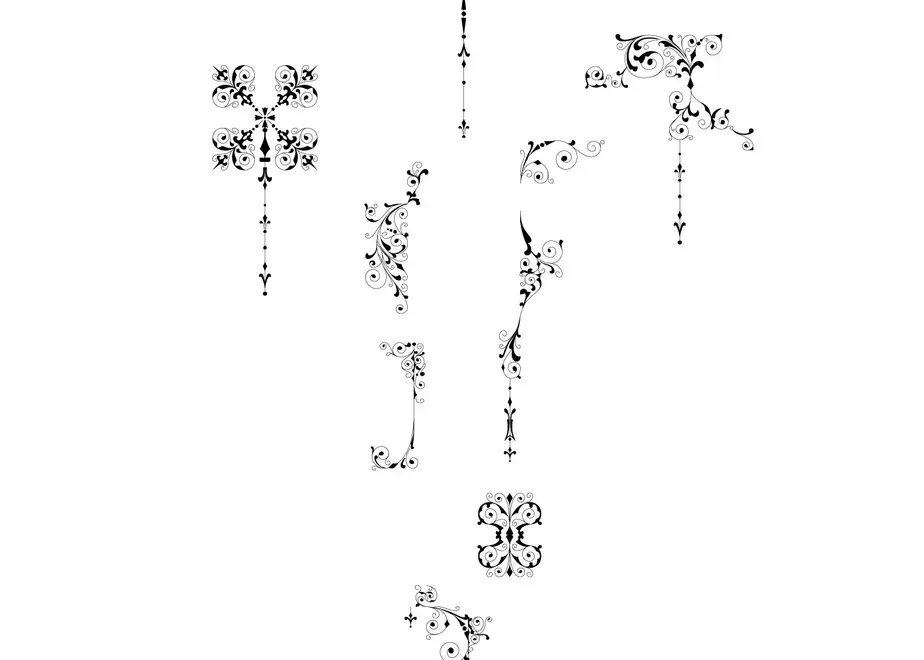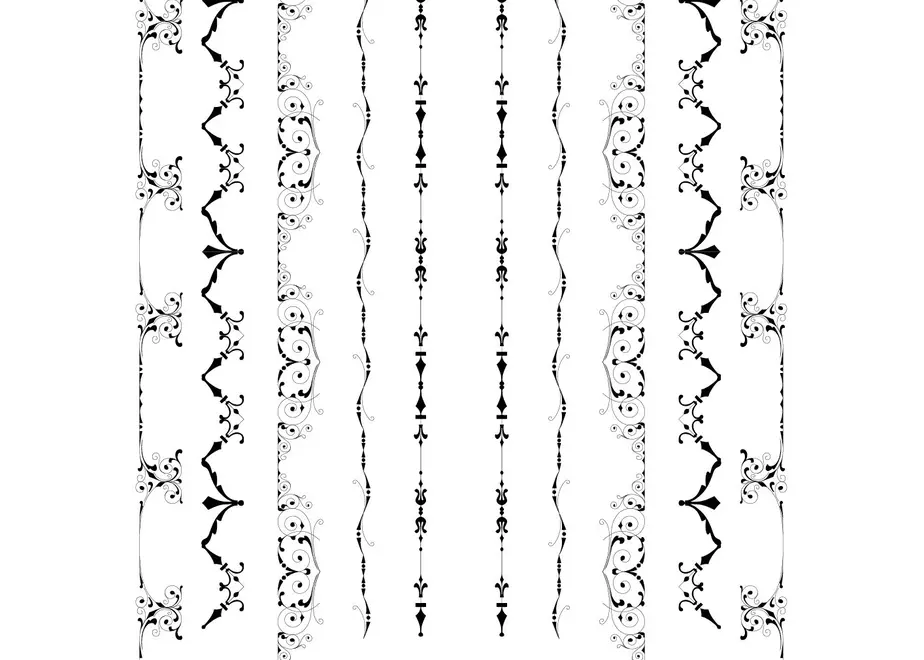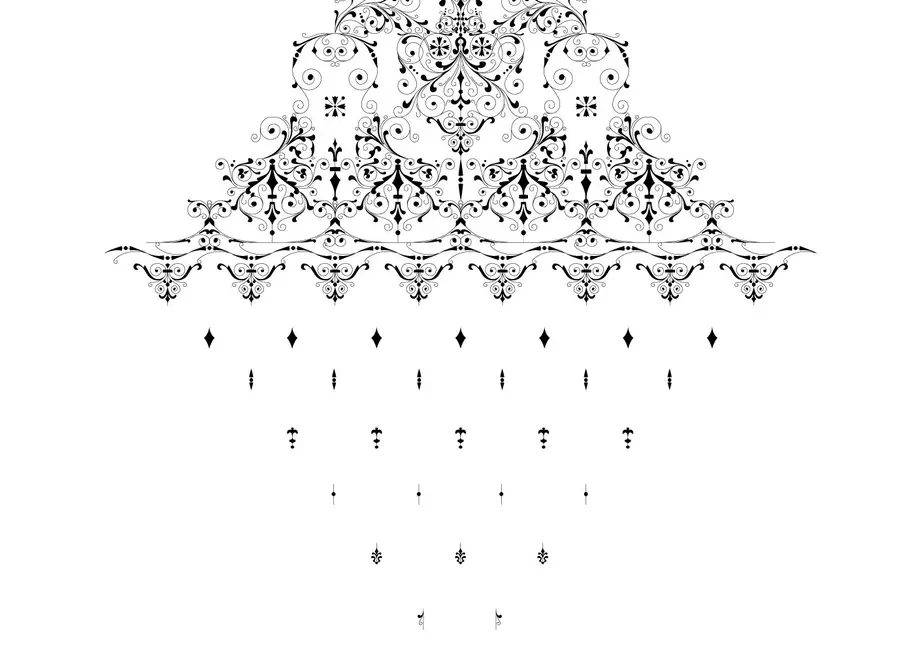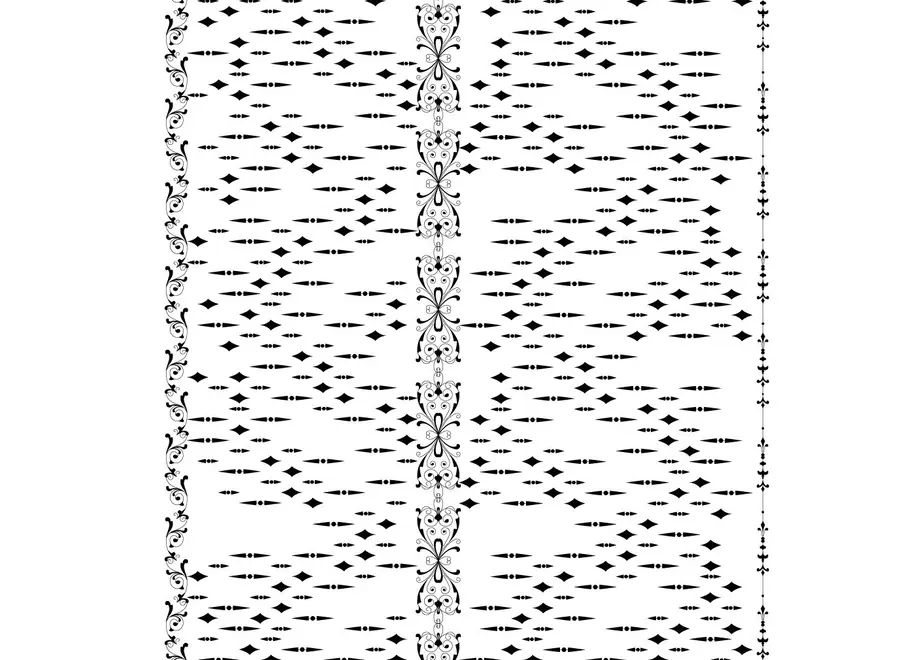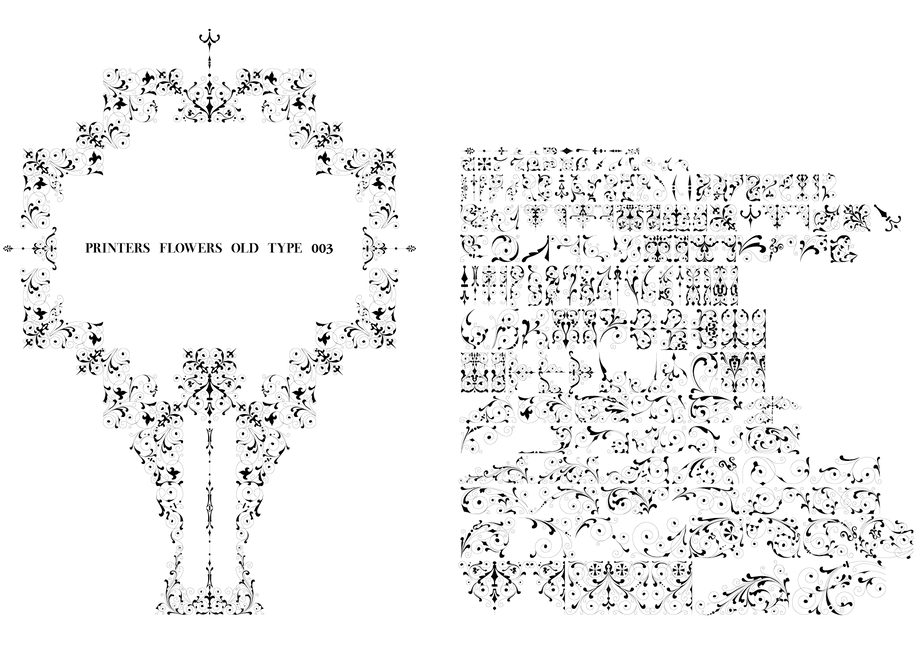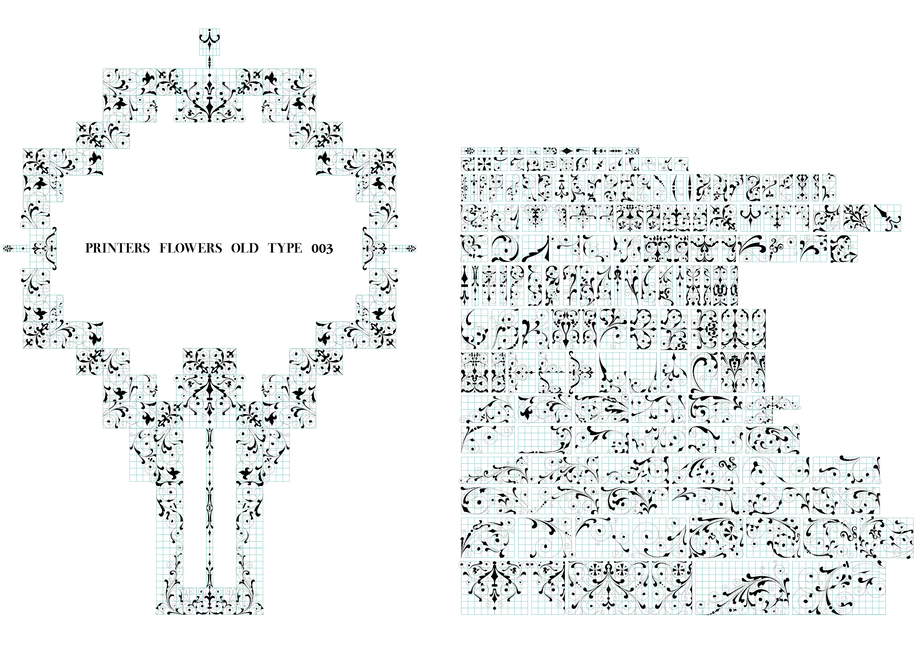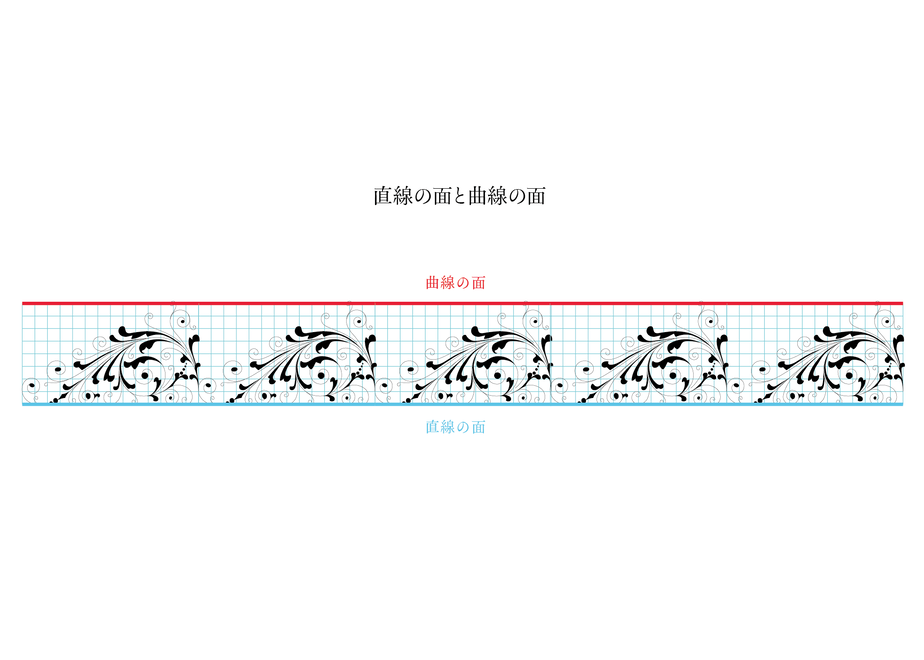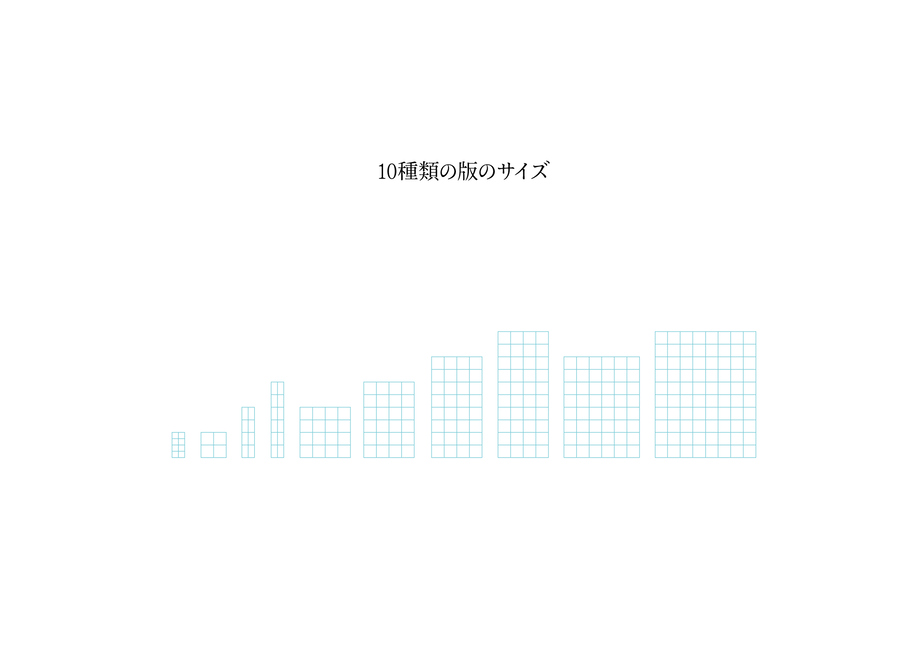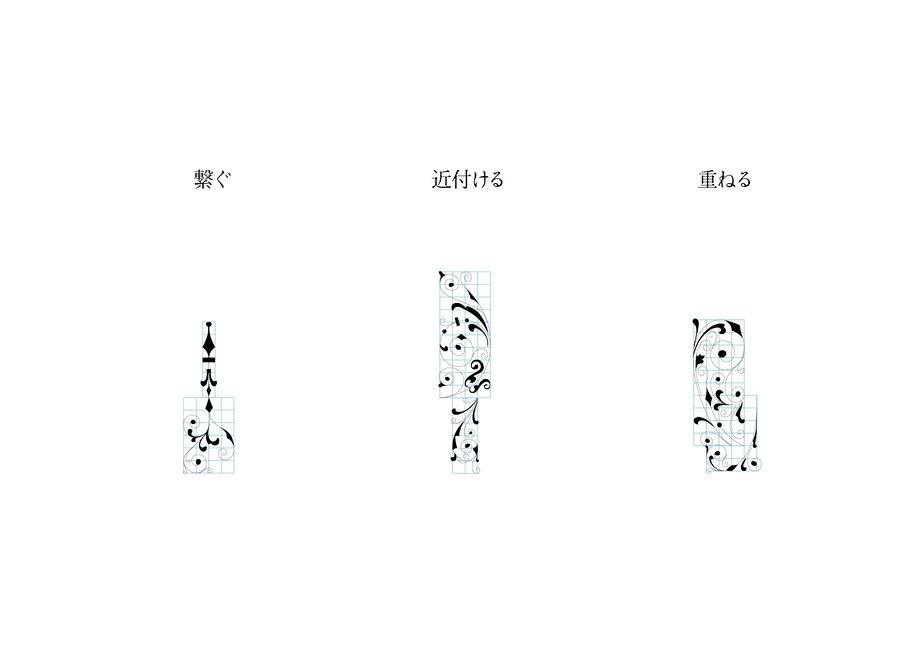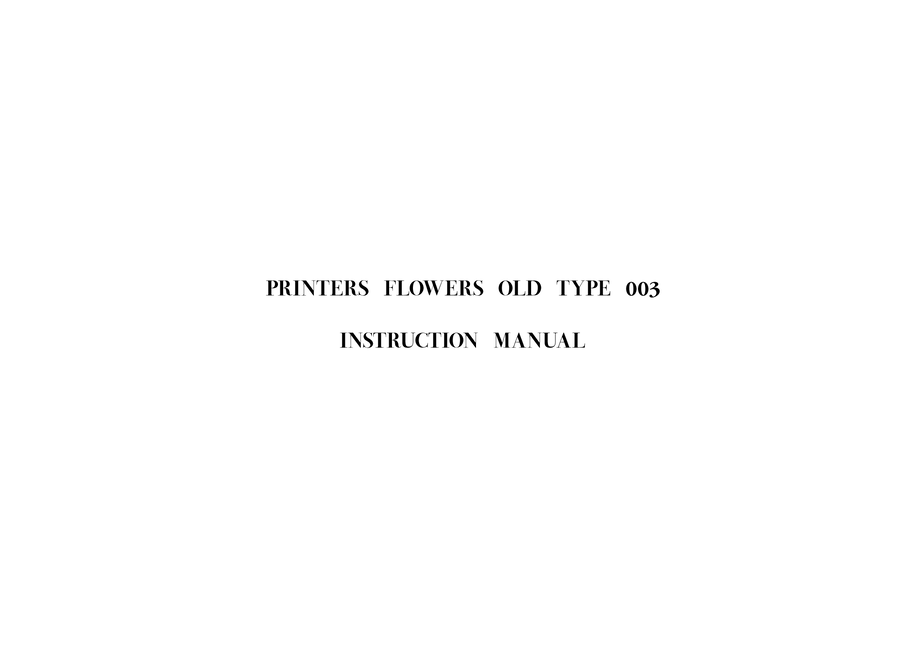
装飾活字:PRINTERS FLOWERS OLD TYPE 003
164 types of decorations with different shapes are made using square units.
Can be used in any combination.
形の違う164種類の装飾を四角のユニットを利用して、
自由に組み合わせて使用出来ます。